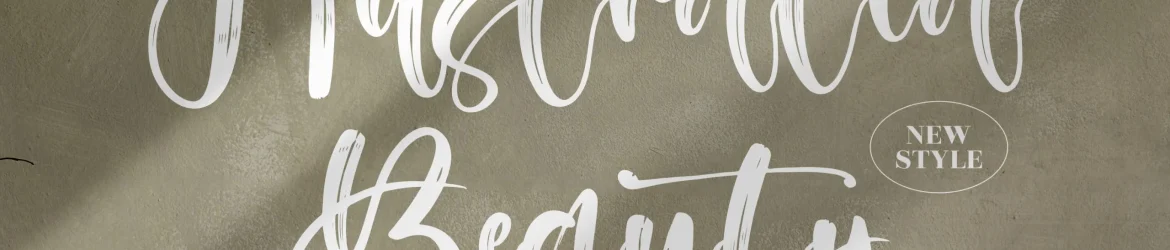
Australia Beauty Font – Download Grátis
A fonte ‘Australia Beauty Font’ é uma fonte escrita a mão criada para designers que desejam incorporar um toque elegante ao seu trabalho. Ideal para projetos variados como logotipos, embalagens de produtos e design de móveis de casa, esta fonte também pode ser usada em designs de etiquetas, cartões de nome, convites, cartas de cumprimentos e até mesmo nas capas de livros. Seu charme peculiar também se destaca em projetos como mugs, camisetas, materiais promocionais, mensagens personalizadas e até mesmo na fotografia e no uso como marca d’água para eventos especiais. Com a capacidade de dar um toque autêntico aos seus designs, ‘Australia Beauty Font’ pode ser uma excelente escolha para os projetos que buscam um elemento único e sofisticado. Seja em uma loja minimalista ou um estabelecimento de luxo, essa fonte escrita a mão é certamente o item perfeito para dar aquele toque especial a qualquer projeto.